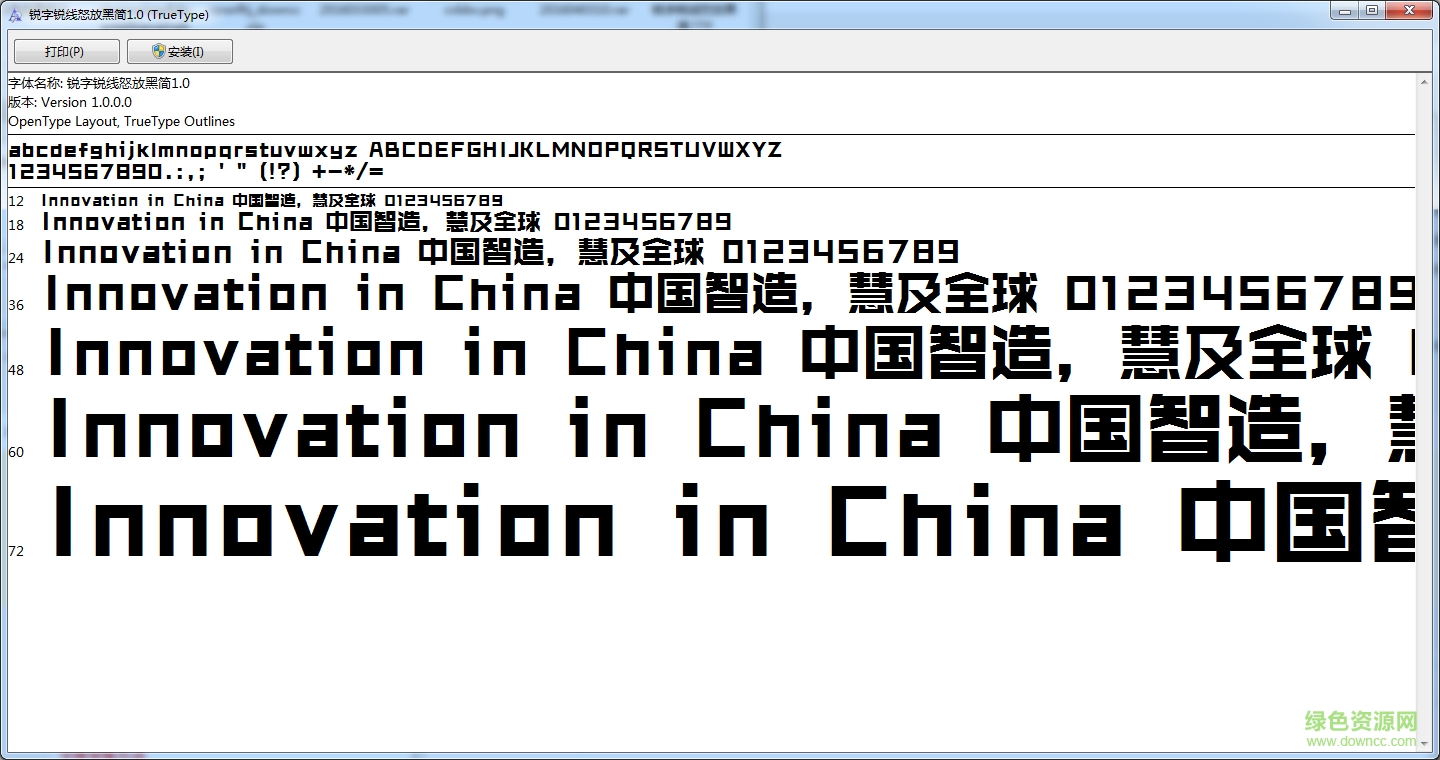
bigruixianblackgbv1.0字體
bigruixianblackgbv1.0字體又名銳字銳線怒放黑簡字體,是一款由銳字工房打造的特色字體,字體構造極富創(chuàng)意,表現(xiàn)形式新穎,使用效果驚艷,需要的朋友快來下載吧!
字體設計特點
字體設計運用夸張、明暗、增減筆劃形象、裝飾等手法,以豐富的想象力,重新構成字形,既加強文字的特征,又豐富了標準字體的內涵。